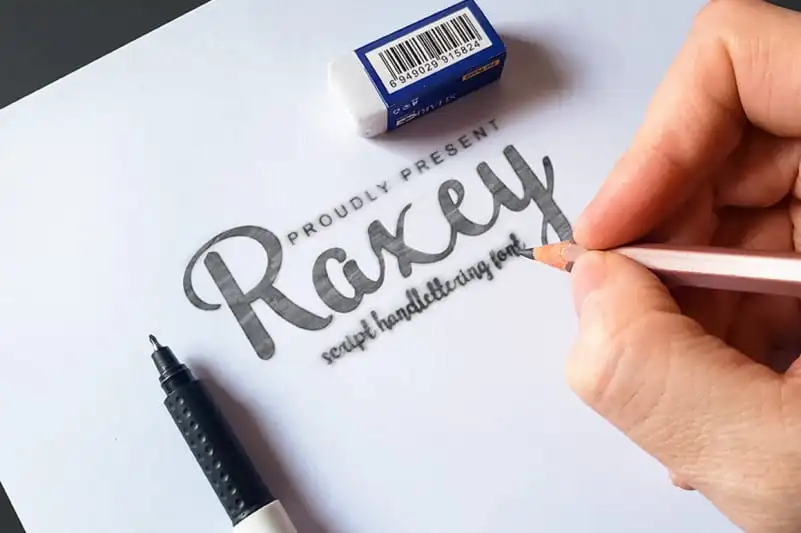
A fonte Raxey Script é uma maravilha de estilo handwritten que foi cuidadosamente criada com um toque de elegância. Desenvolvida pela designer twinletter, ela se destaca como uma opção perfeita para diversos projetos de design, incluindo marca, títulos, designs para casamentos, convites, assinaturas, logotipos e etiquetas, entre outros. A Raxey Script é mais do que apenas uma fonte. Ela traz a essência de um autêntico traçado com mão livre à sua identidade visual, fornecendo o toque personalizado necessário para dar vida aos seus projetos design. Este script gráfico é perfeito para quem busca expressar seu estilo único e sua personalidade através da tipografia, seja em uma camiseta de campanha ou um logo exclusivo. Com Raxey Script na sua arsenal de ferramentas, você terá a capacidade de criar trabalhos que não apenas destacam, mas também elevam o nível do design. Essa fonte é mais do que uma escolha estética; ela é uma maneira de expressar sua visão única através da tipografia.